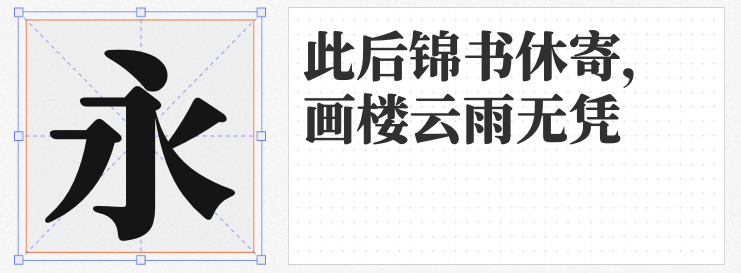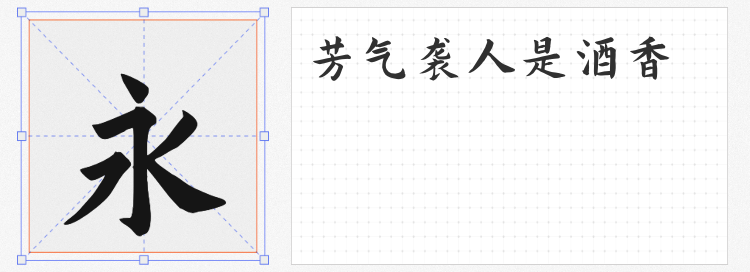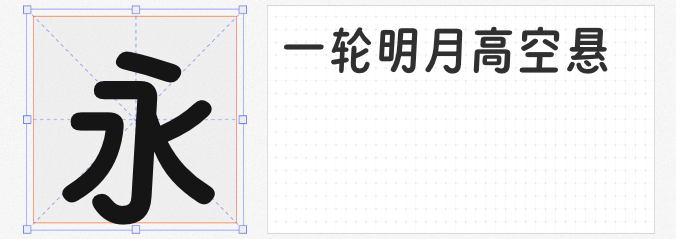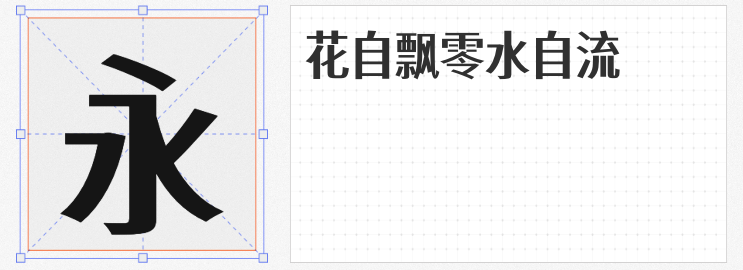
四款免费商用字体:让海报设计既有古韵又具现代张力
在海报设计中,字体不仅是信息载体,更是视觉风格的灵魂。若想兼顾文化底蕴与现代审美,同时规避版权风险,以下四款基于开源字体改造的「寒蝉」免费商用字体值得收藏。它们均采用 SIL Open Font License 1.1 协议,支持个人与企业免费商用,且针对海报场景优化了字形、字重与排版特性。
1. 寒蝉团圆体 圆体
作为得意黑的二创字体,寒蝉团圆体以 3°倾斜角度 打破传统黑体的静态感,赋予文字跃动张力。其笔画粗细对比强烈,横竖转折处保留黑体的硬朗,但通过微倾斜设计弱化机械感,适合科技、运动、潮流类海报。新增的竖排优化特性,让长文案在纵向布局中更显秩序,例如音乐节海报的演出时间表或品牌标语。
2. 寒蝉锦书宋 Heavy
基于思源宋体改造的寒蝉锦书宋 Heavy,通过 圆角处理 与 字重重构 ,将宋体的文人气质转化为现代设计语言。其笔画粗细均衡,中宫开阔,即使放大至海报标题尺寸仍保持清晰可读性。温润的圆角设计适合文化、教育类海报,如书店促销、艺术展览的标题;而 Heavy 字重的厚重感,又能为奢侈品或高端活动的海报增添庄重感。
3. 寒蝉书体·春秋 秋鸿
以开源字体「演示秋鸿楷」为基底,寒蝉书体·春秋 秋鸿保留了楷体的书法笔意,起笔收锋处自然流畅,字形结构疏密有致。其古色古香的韵味,是中式海报的绝佳选择:茶饮品牌推广可借用其飘逸感传递禅意;传统节日活动(如中秋、春节)的主视觉标题,也能通过楷体的书写性强化文化认同。
4. 寒蝉有机体 Medium
寒蝉有机体 Medium 以思源黑体为原型,通过逆反差设计颠覆传统黑体的视觉逻辑——横细竖粗的强烈对比,营造出类似金属压印的立体效果。这种前卫风格适合科技、游戏、实验艺术类海报,例如电竞比赛的赛博朋克风标题,或未来感产品发布会的视觉主轴。其 Medium 字重平衡了存在感与精致度,避免过粗笔画在复杂背景中显得笨拙。
这四款字体不仅免费,更通过细节优化解决了开源字体在海报设计中的常见痛点——如竖排不齐、字重失衡、风格单一等。设计师可放心将其纳入素材库,为创意提供更自由的表达空间。